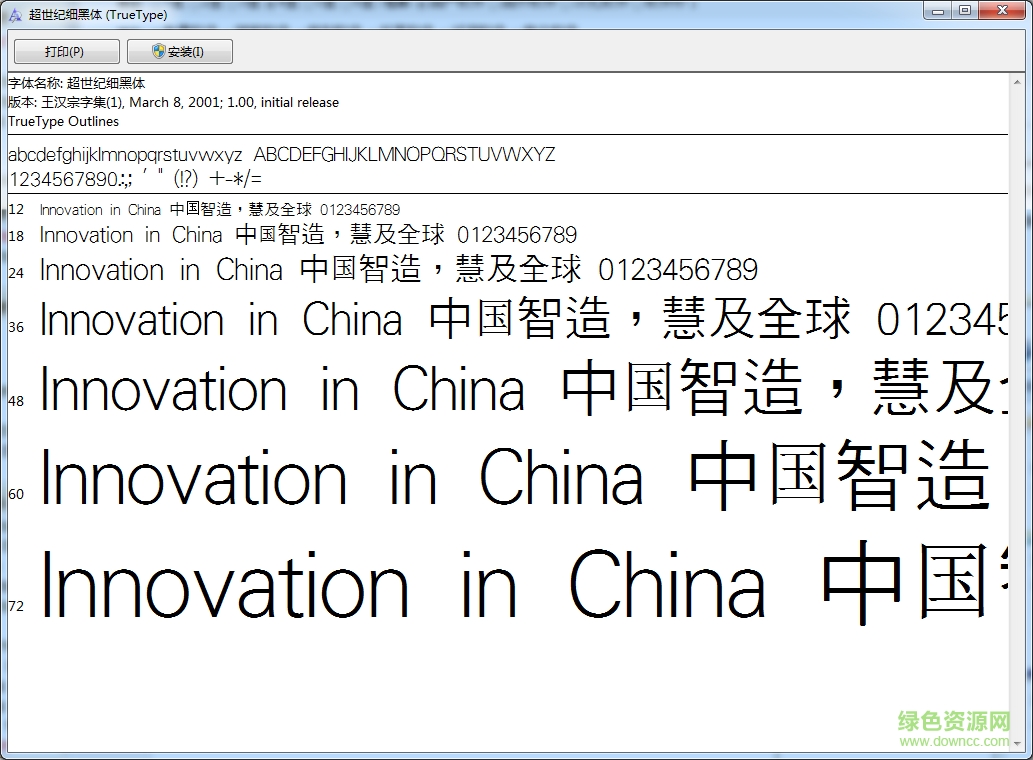
超世紀細黑體是一款非常美觀的超世紀字體軟件,字體簡潔大方彰顯個性,常用于廣告設計、圖文印刷等多種領域,應用廣泛非常便捷??靵砭G色資源網(wǎng)下載體驗吧!
等線比較相似,只是方正細等線比方正細黑還要細,常用于時尚雜志的正文,方正細黑與方正細等線筆畫橫平豎直、結(jié)構(gòu)醒目嚴密、便于閱讀,所以時尚雜志中比較常見,當然,這一類字體不適宜在報廣(報紙廣告)的文字選擇,因為報廣印刷粗糙,細黑幾乎無法識別,但是在印刷精美的一些時尚雜志中,細黑與細等線會表現(xiàn)的非常精美。的外形比宋體要“方”、端正,不失時代氣息也極具傳統(tǒng)味道。所以方正報宋和方正宋一簡體也常用出現(xiàn)在一些時尚雜志的正文中。以上兩種字體比較適合和銅版紙,啞粉紙,道林紙配合使用。審美要比黑體的高雅很多。在海報與網(wǎng)站圖標中運用比較多,不適合做正文和標題的選擇,比較適合副標題文字的選擇。